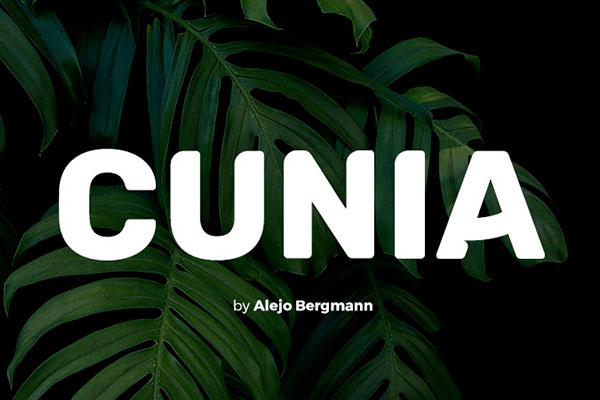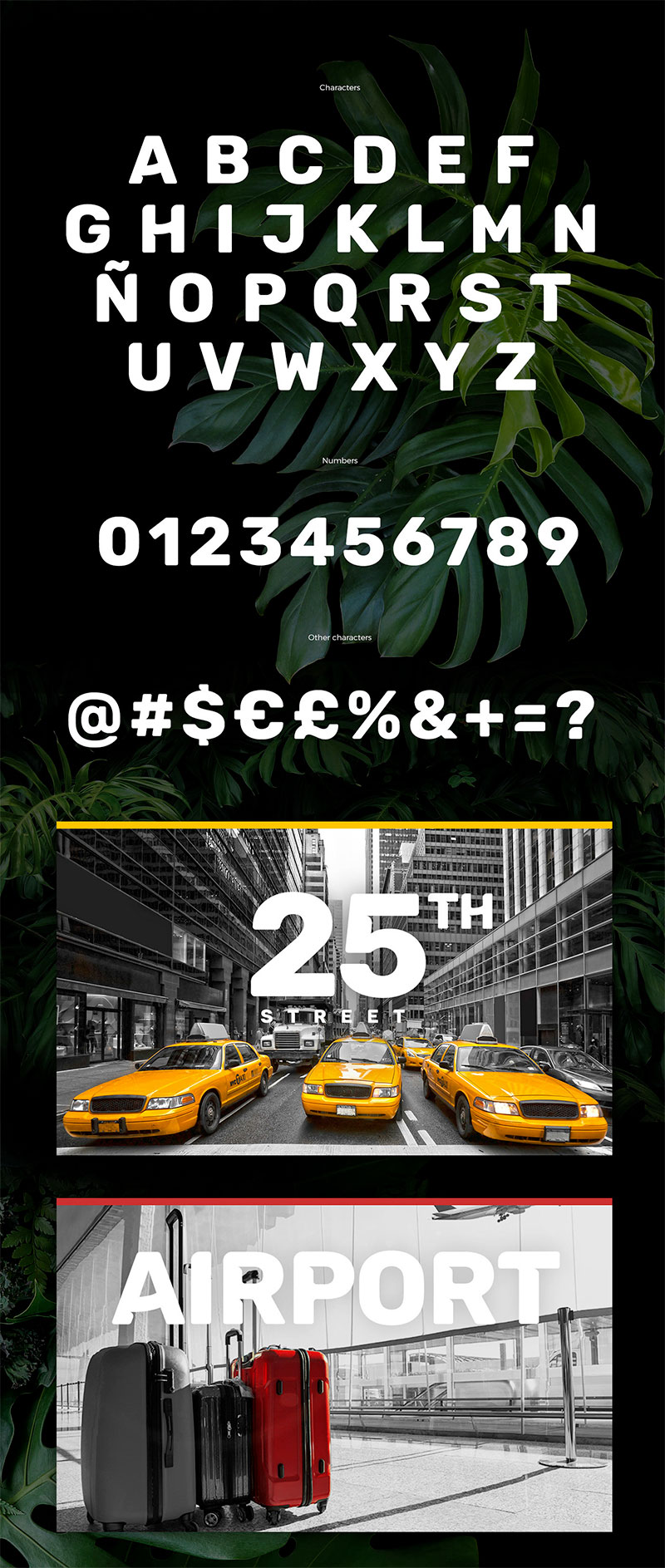
Cunia
Cunia字体:大写无衬线,圆润独特,适用于多种场景
Cunia是一款由Alejo Bergmann设计的独特字体,专为标题而打造。这款大写sans-serif字体以其圆润的特点和优雅的外观,非常适合用于徽标、标签、标题以及各种印刷品等。
Cunia字体的设计赋予了它独特的视觉吸引力,同时又保持了易读性和流畅性。无论是在策划活动、制作宣传物品还是设计商标,Cunia都能为你提供一种时尚而引人注目的呈现方式。
Cunia字体效果预览